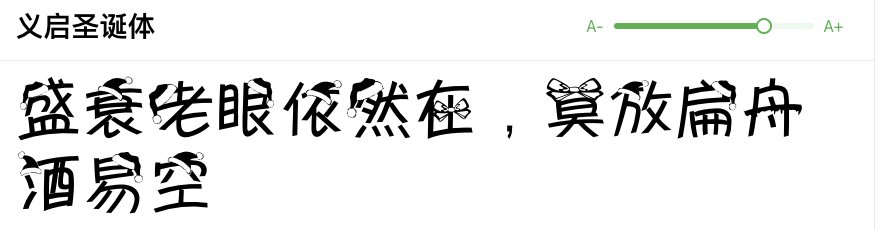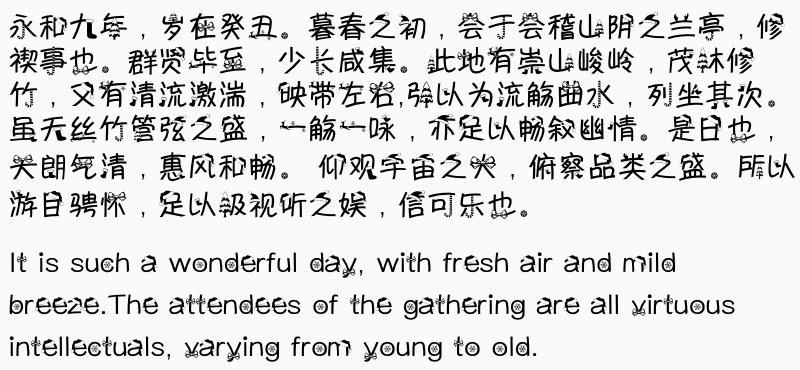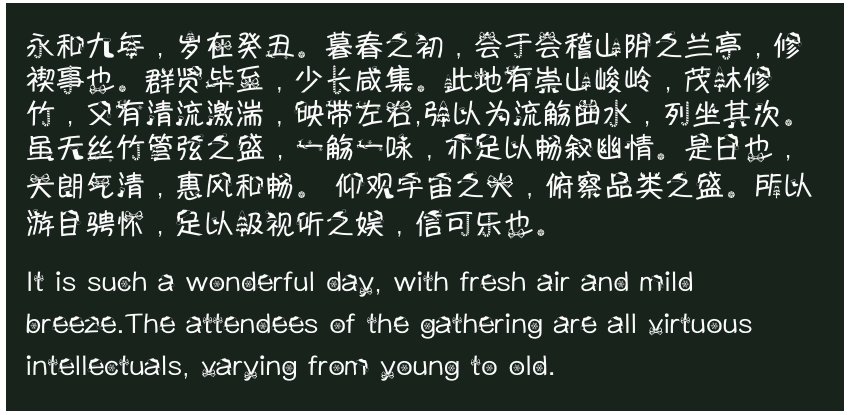
圣诞一年只有一次,期望在下雪的季节当我抬头仰望天空的时候,能看到带着铃铛的麋鹿和满载的圣诞老人。义启字库一款义启圣诞体字体以搞怪又以卖萌的方式成为了一款专门为圣诞节而设计的艺术字体。
义启字库义启圣诞体,让我们每天都是圣诞
圣诞节不可能天天都有,但是义启字库义启圣诞体,让我们每天都是圣诞。义启圣诞体每一个字体都有着不同的圣诞含义,圣诞树是一种,圣诞帽也是一种,还有能受到礼物的圣诞袜,包括有魔法的圣诞手杖都是义启圣诞体表现的根本基础。
义启字库出品了各种适合广告人员pop手写体的义启个性合集字体。从它的理念的幼儿体的理念问世,一直到后来不断地改进又改进,不断地演化再演化,变成了越来越成熟的趋势,受到了很多广告事业人员的喜爱,演变的个性类型也越来越多,它们紧跟着热点紧跟着时尚又紧跟着节庆日子,衍生出了萌妹体,心宽体等等等等。